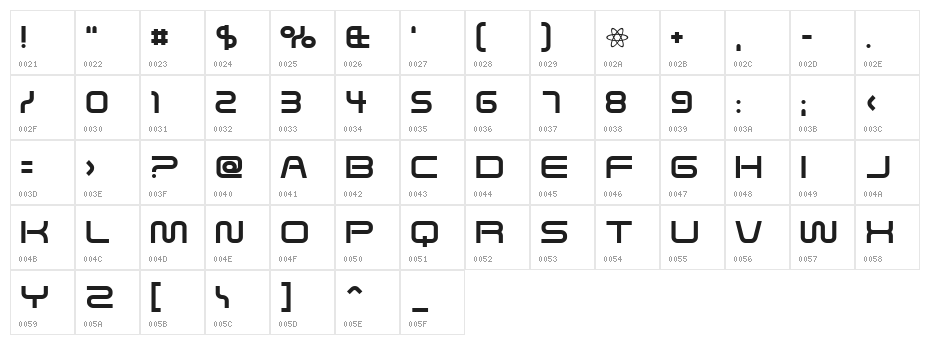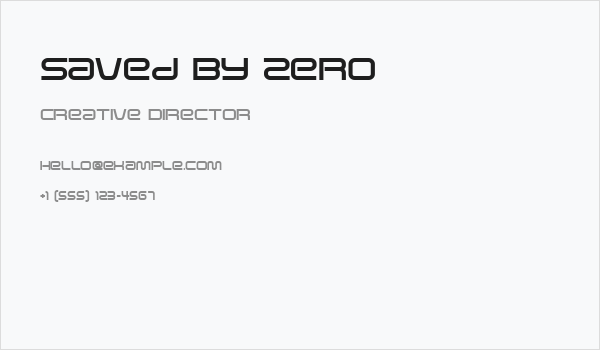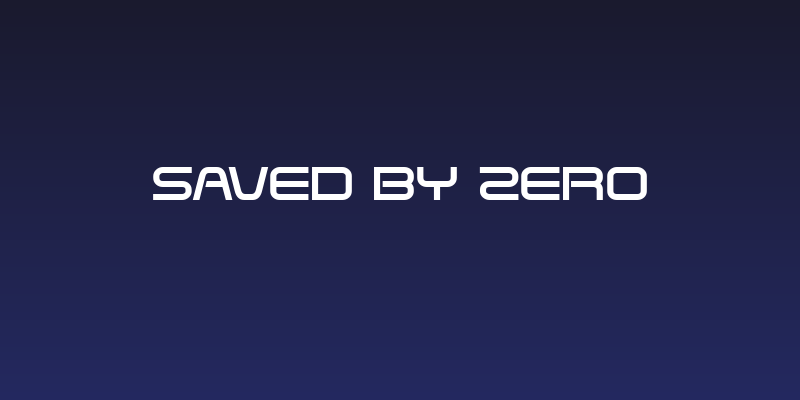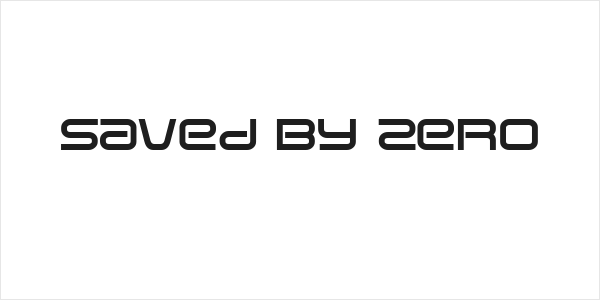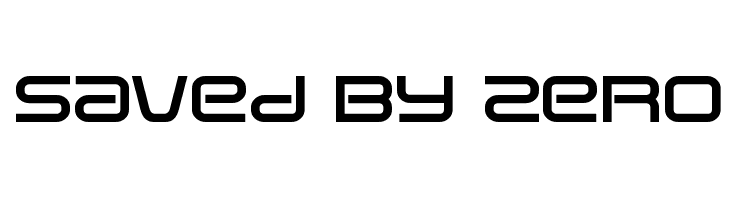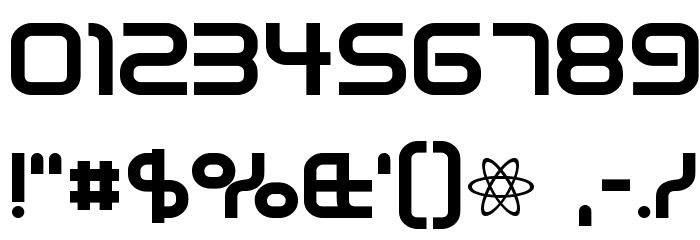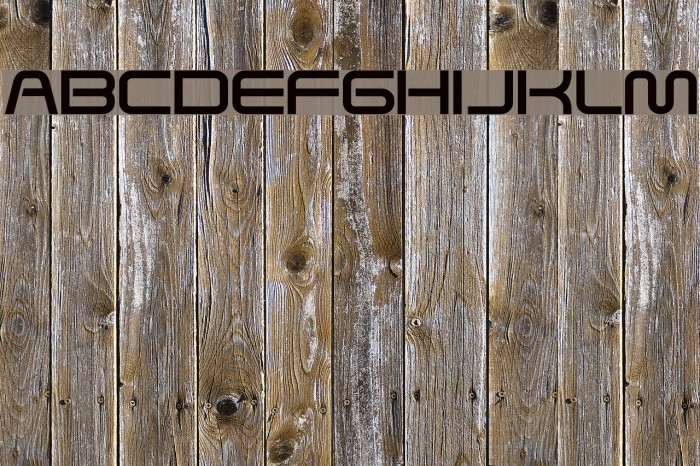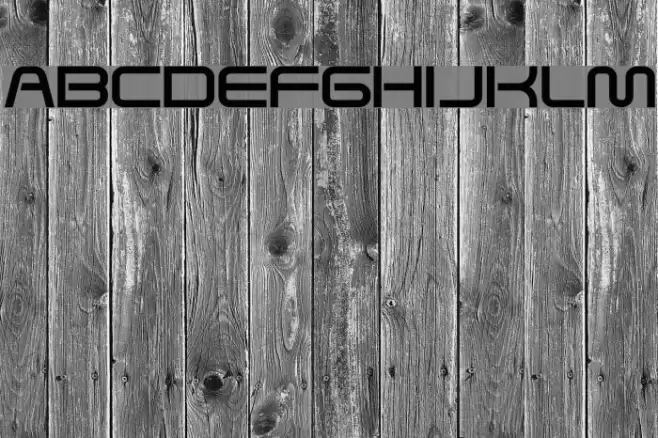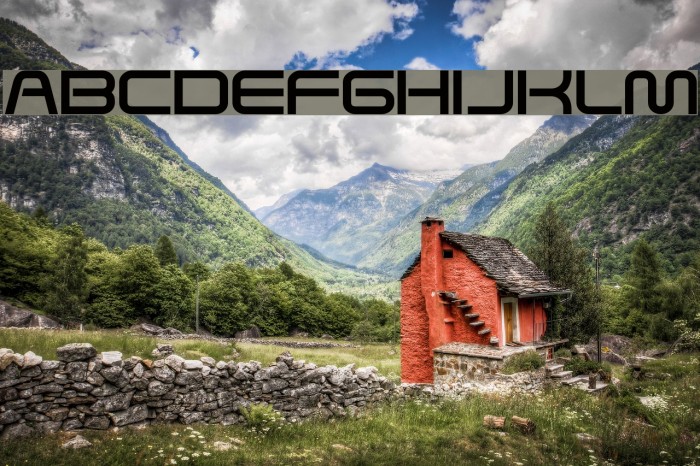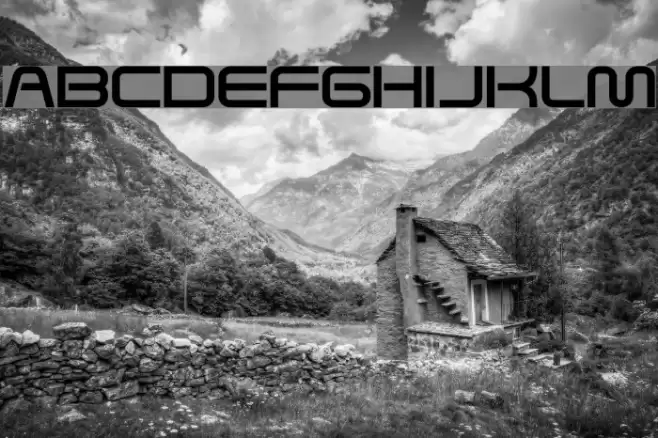
Saved By Zero Font
| Caso de uso | Logos, Headlines, Digital Interfaces |
| Proyectos propuestos | Ideal for technology branding, digital interfaces, sci-fi themed projects, and modern advertising. |